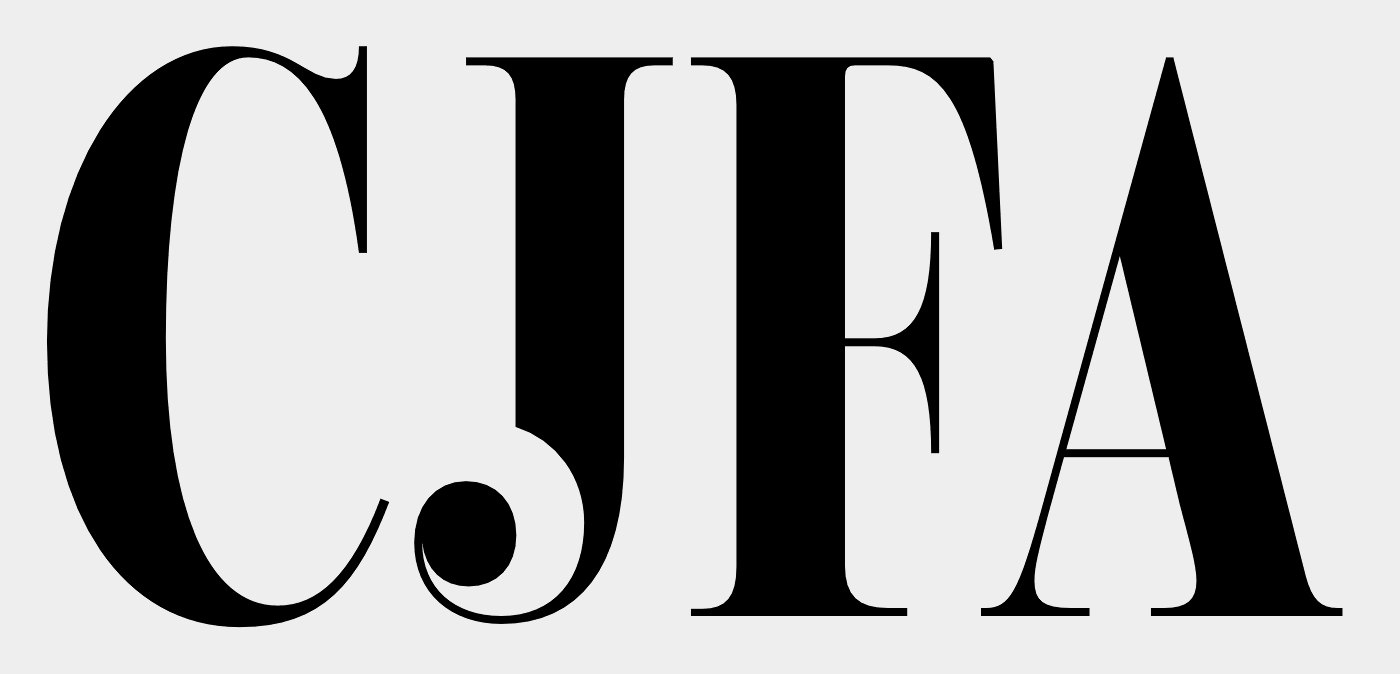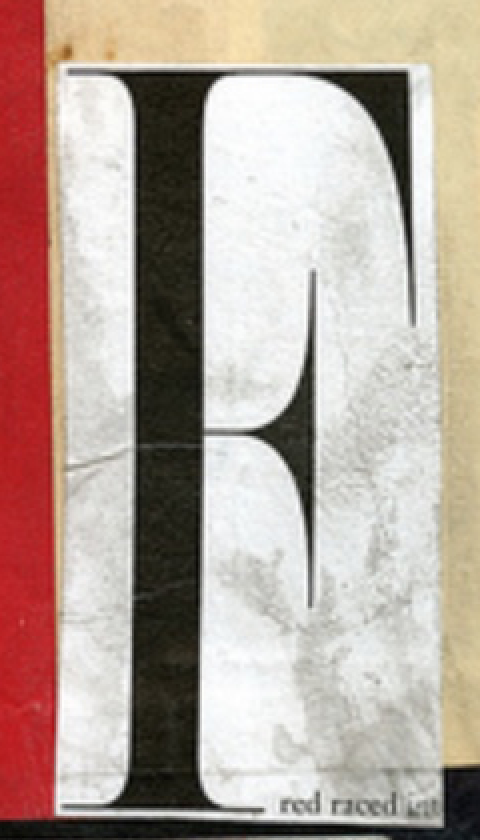
Um es mal grob einzuordnen, geht es stilistisch in Richtung der hier gezeigten klassizistischen Antiquas. Wenn Du bei einem der großen Schriftanbieter Suchworte wie »Didone« und »klassizistisch« eingibst, dann werden Dir eine Vielzahl von Treffern angezeigt, die Du dann sichten kannst auf der Suche nach genau diesem schmalen Schnitt. Es kann aber auch sein, dass es sich hier um keinen ursprünglich so gefertigten Schriftschnitt handelt, sondern dass ein normalbreiter Schnitt zusätzlich in der Breite gestaucht wurde. Sehr gut möglich ist, dass es sich bei dem von Dir gezeigten Beispiel um einen Displayschnitt handelt; dafür sprechen die extrem ausgeprägten Strichstärkenunterschiede und die kurvigen Übergänge zwischen Geraden und Serifen.
Dieser Font kommt meinen Vorstellungen sehr Nahe. Ich benötige für graphische Zwecke 4 Buchstaben : C, F, A, J . Wenn Du Zugang zu den Buchstaben hast, wäre ich sehr dankbar, wenn Du mir die zukommen lassen würdest.
ich besitze keine Lizenz der Encorpada, deswegen kann ich Dir da leider  nicht helfen. Ich kann Dir nur mittels des hier im Forum verwendeten MyFonts-Preview-Tools zeigen, wie die von Dir benötigten Buchstaben in der Encorpada aussehen: